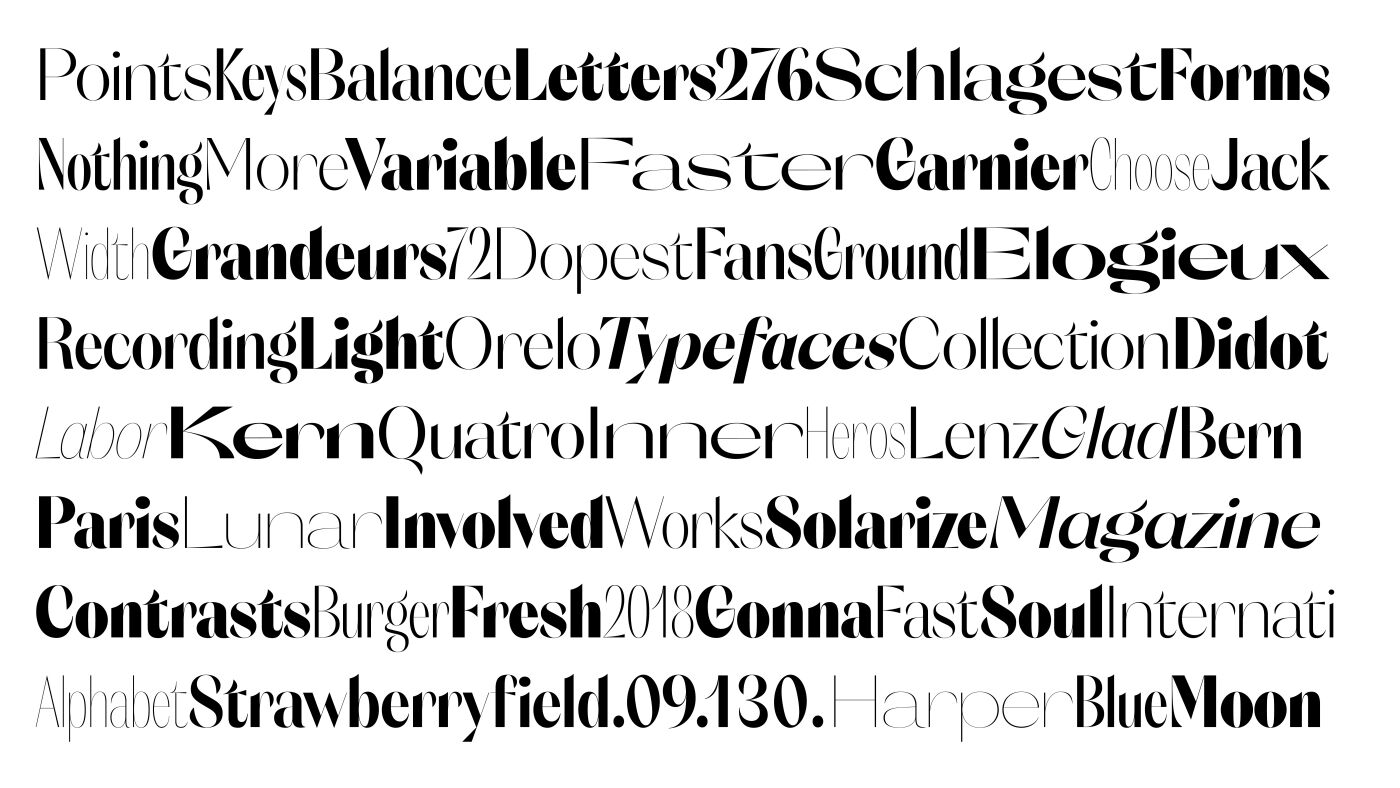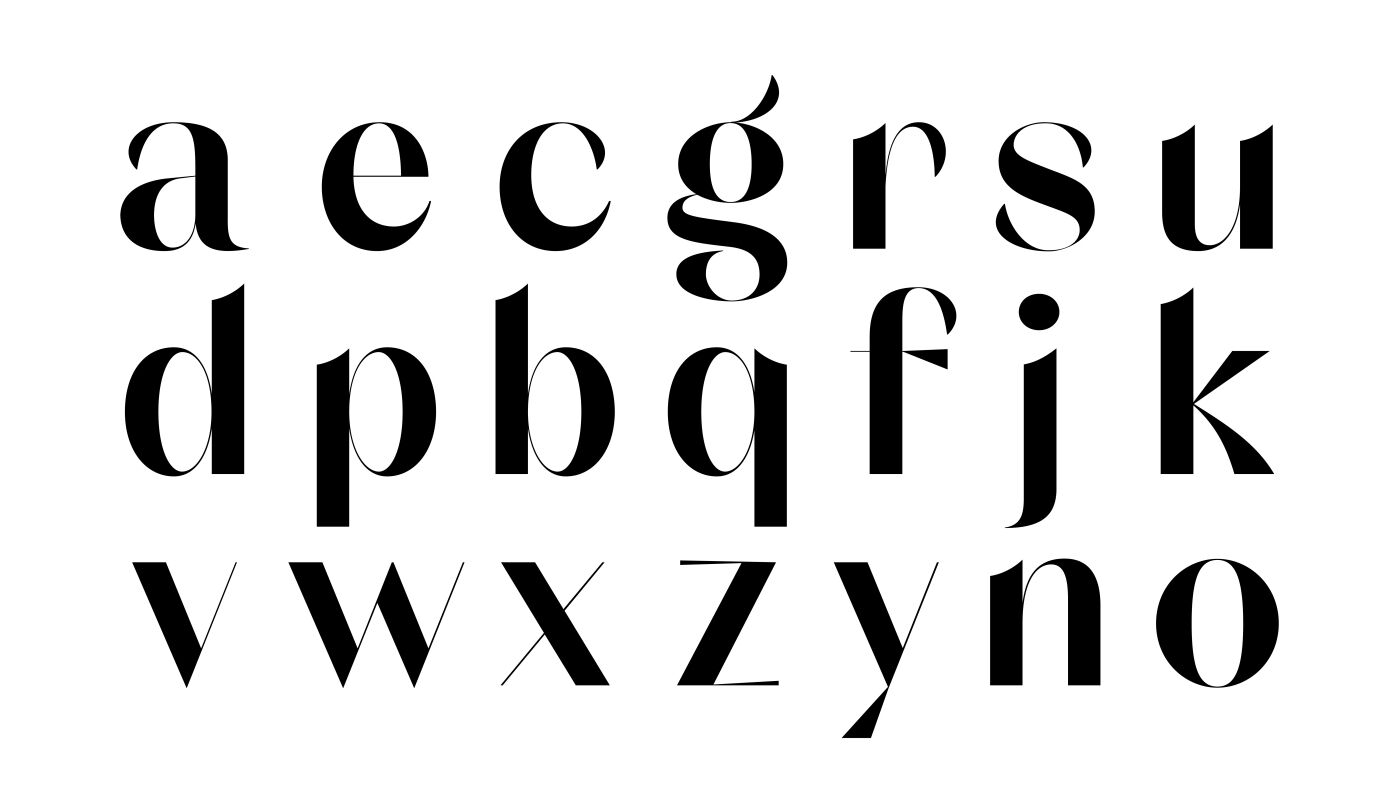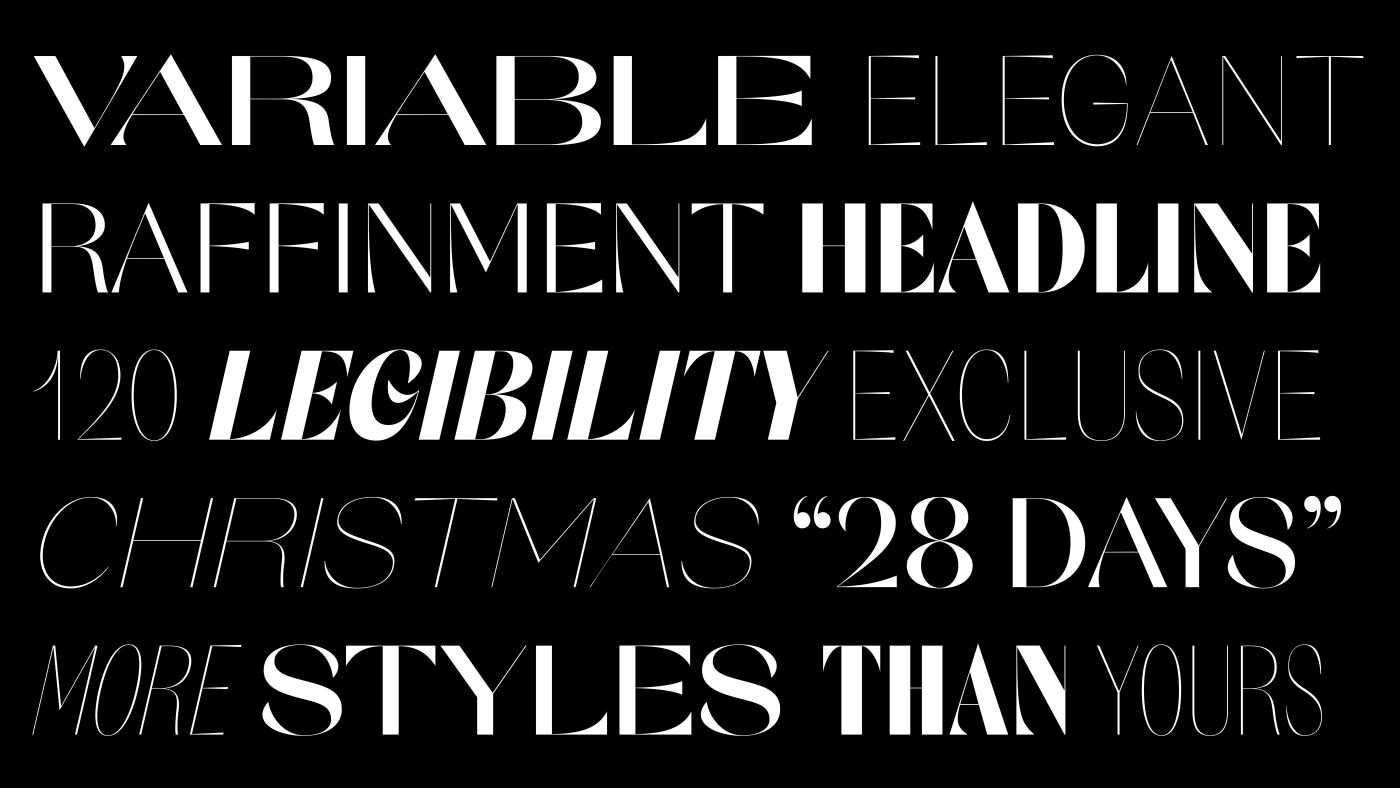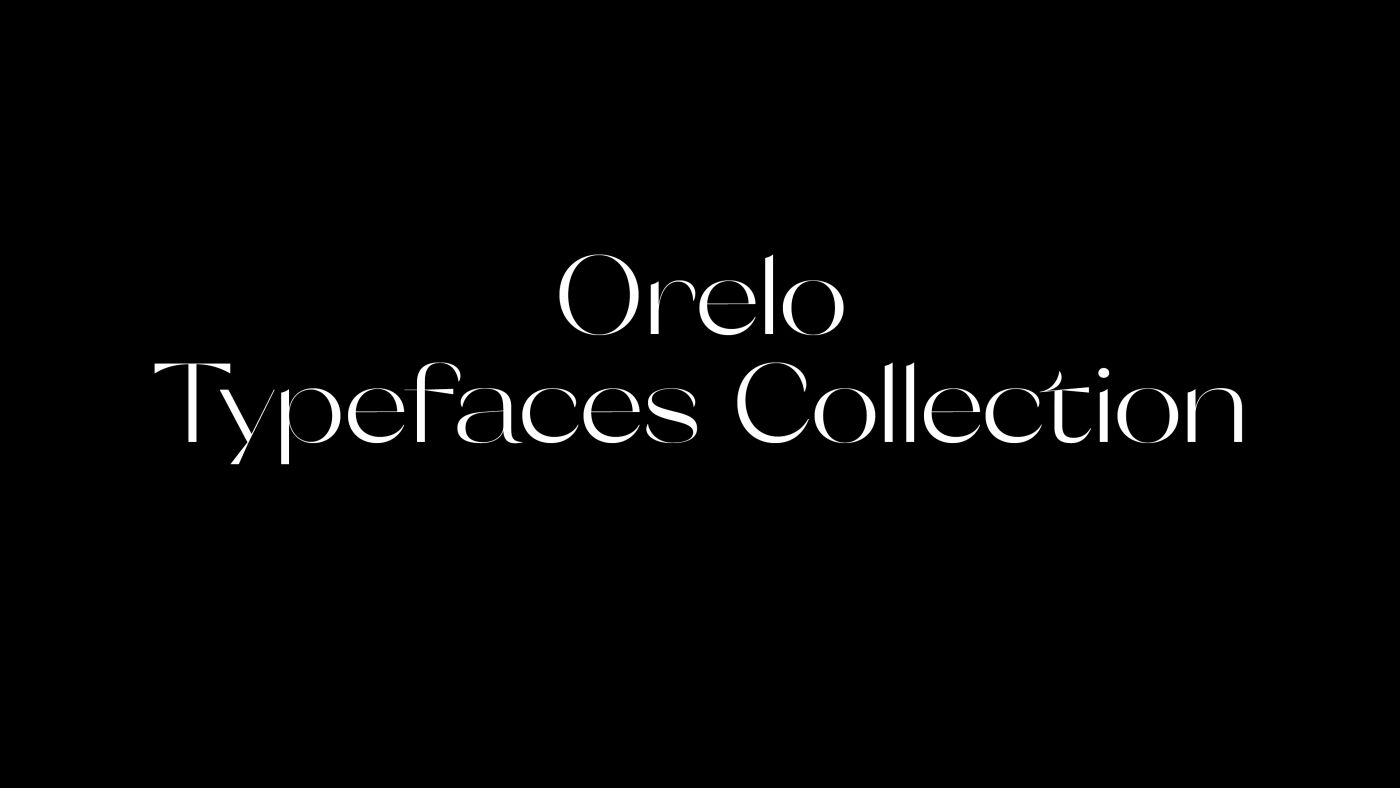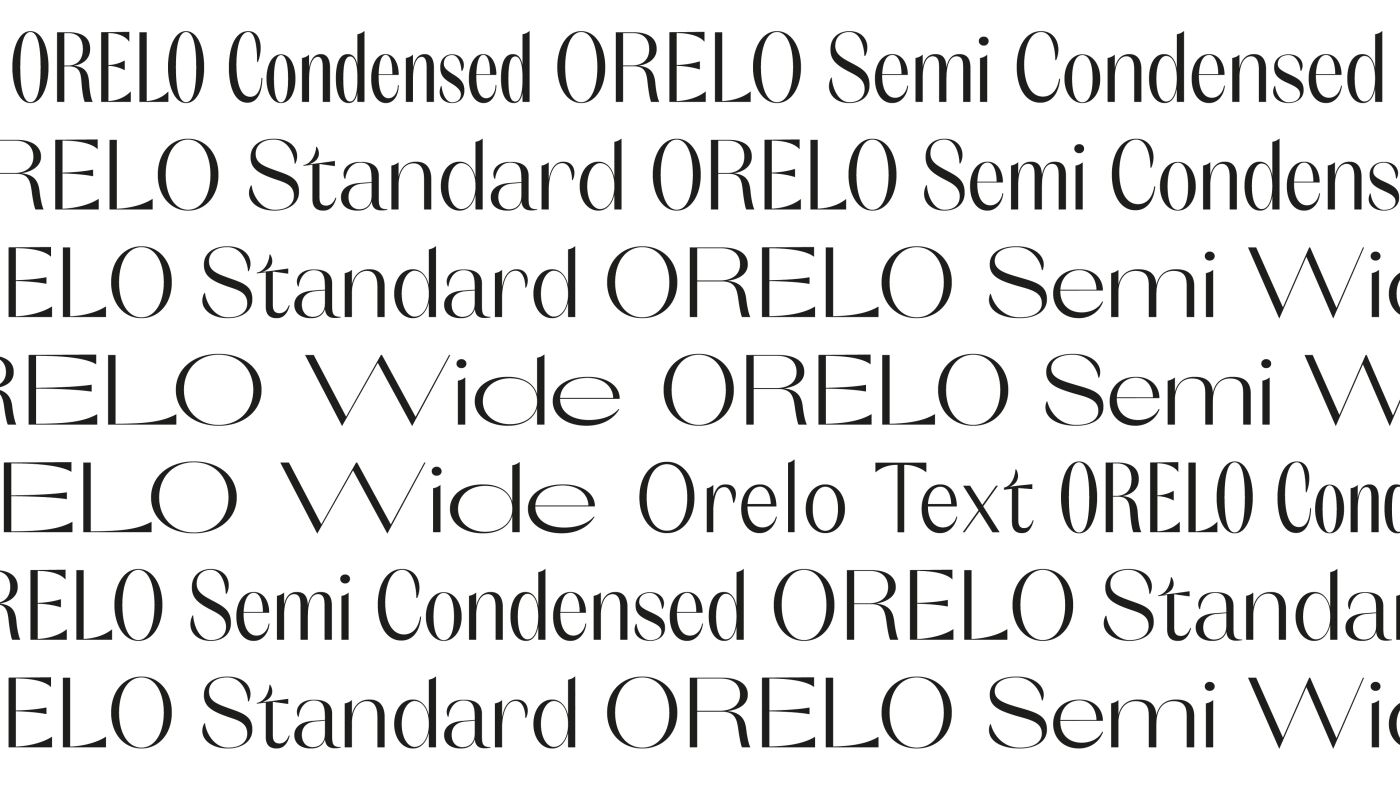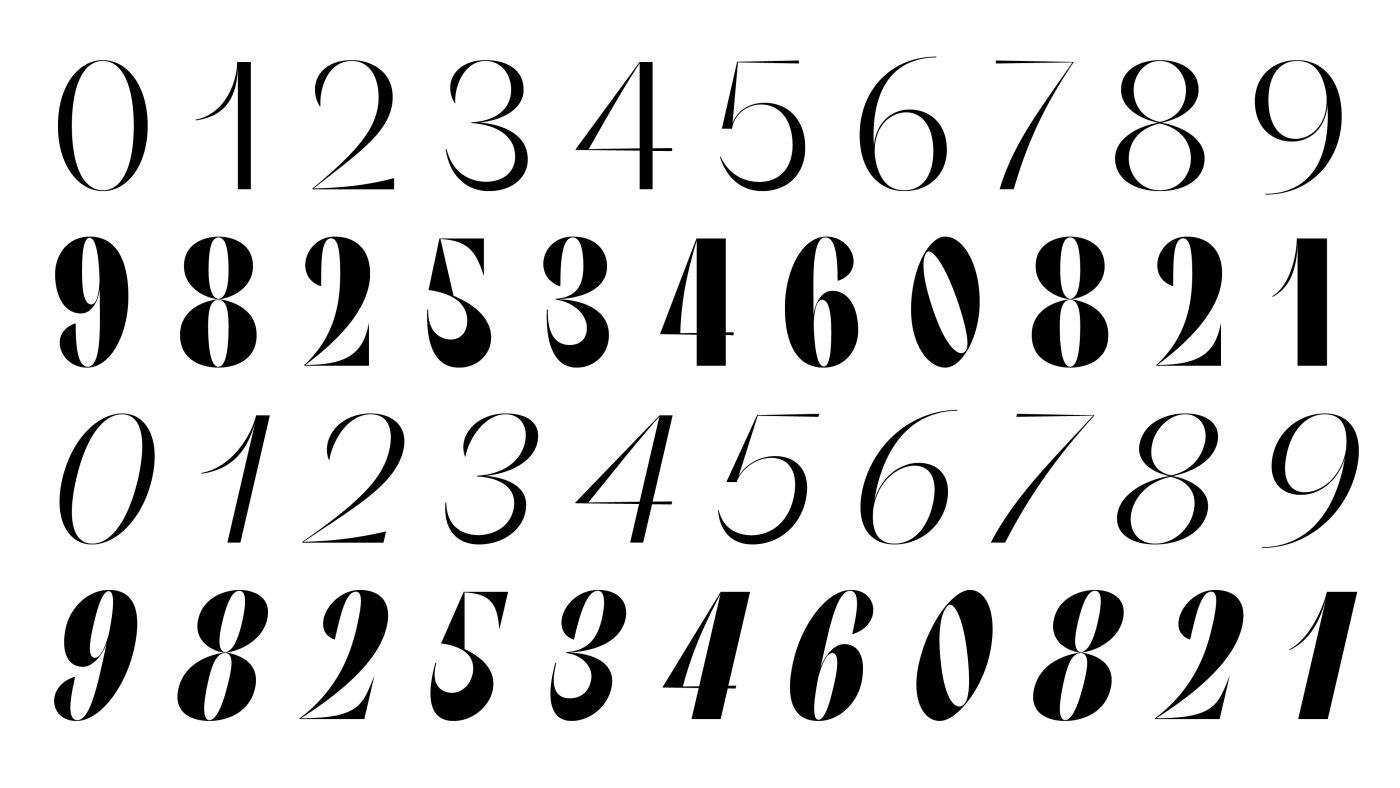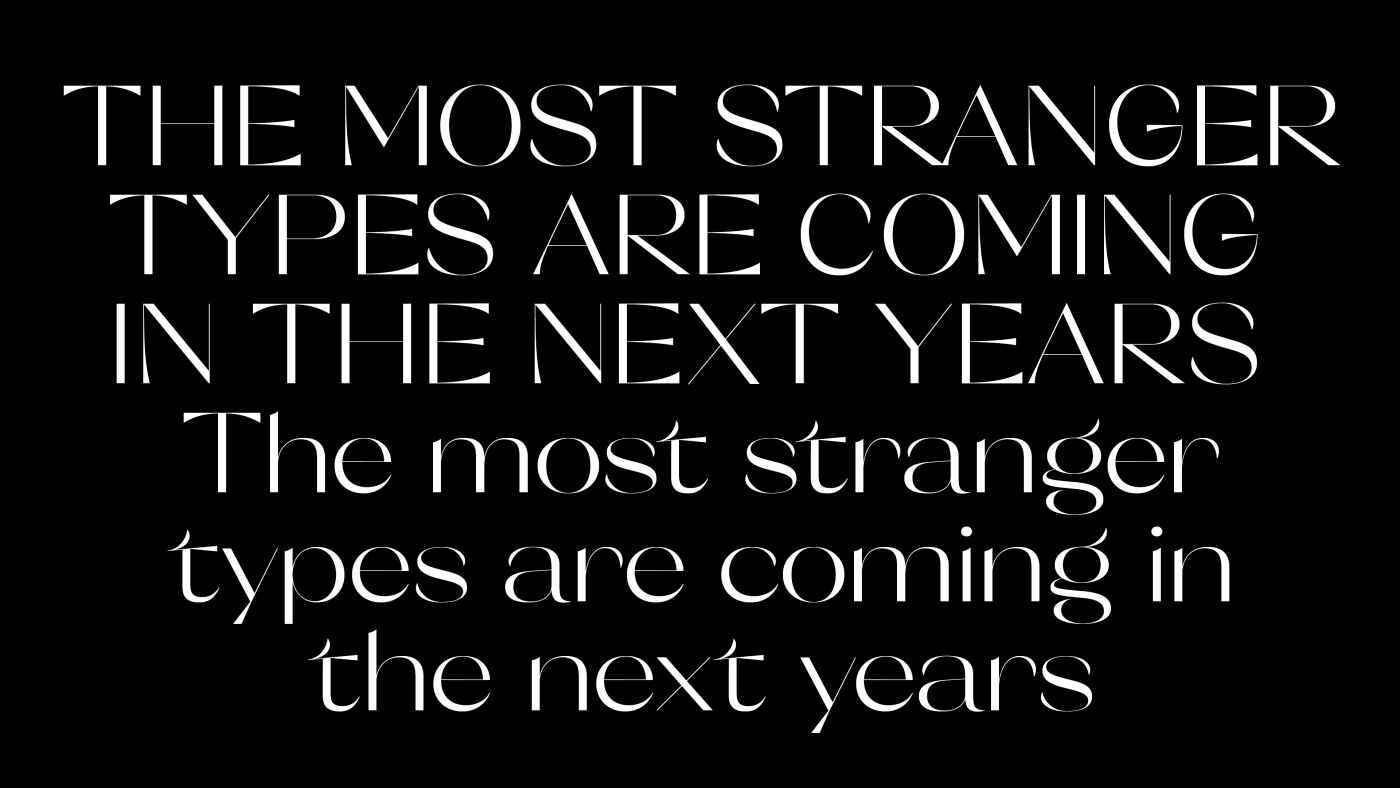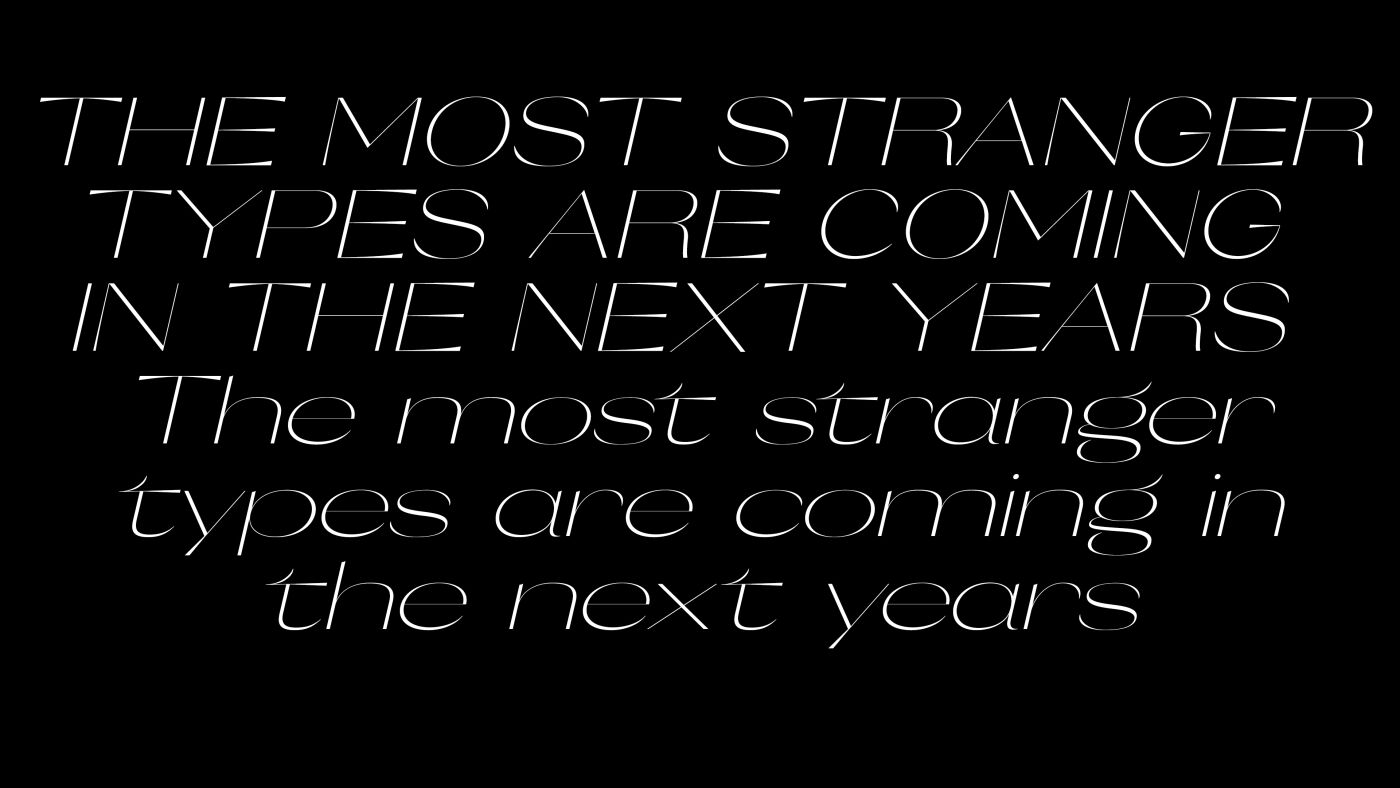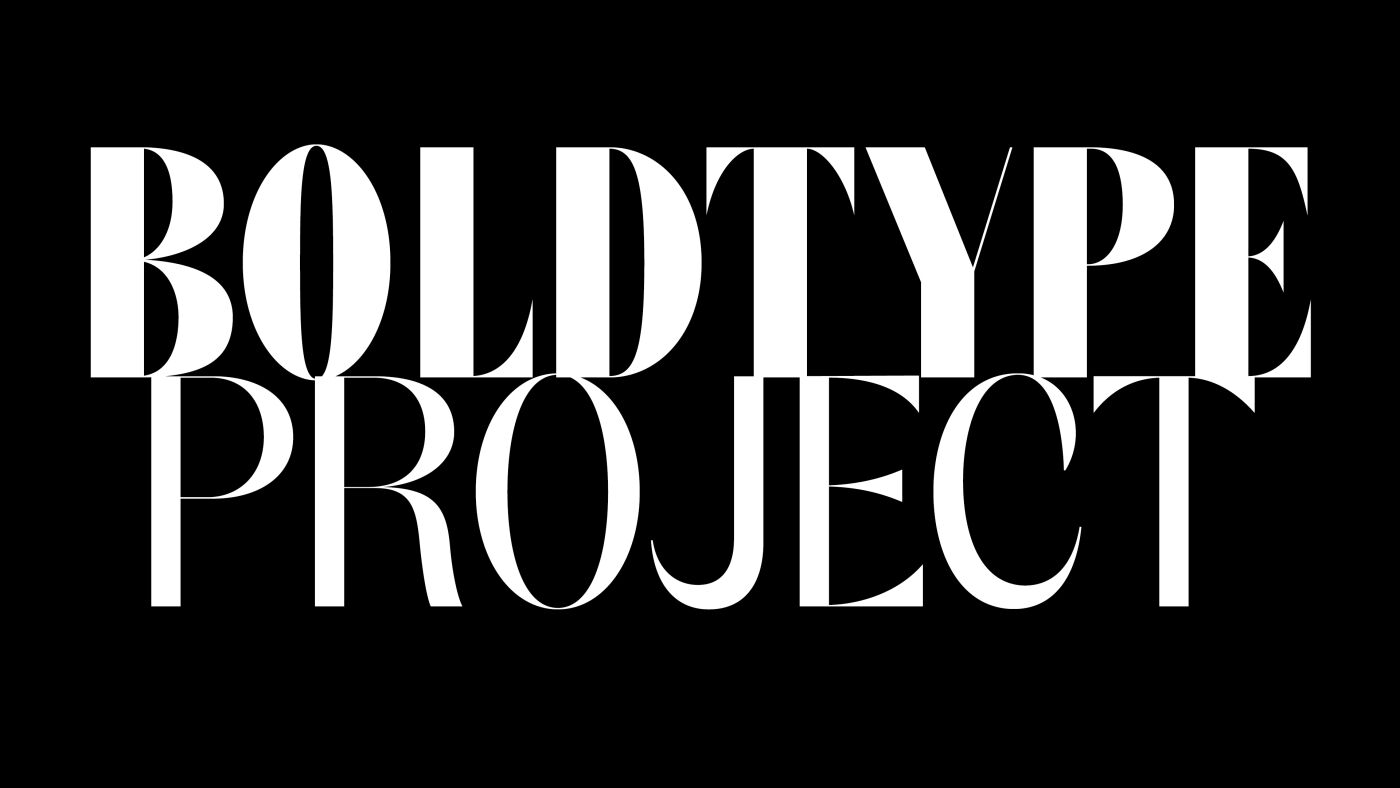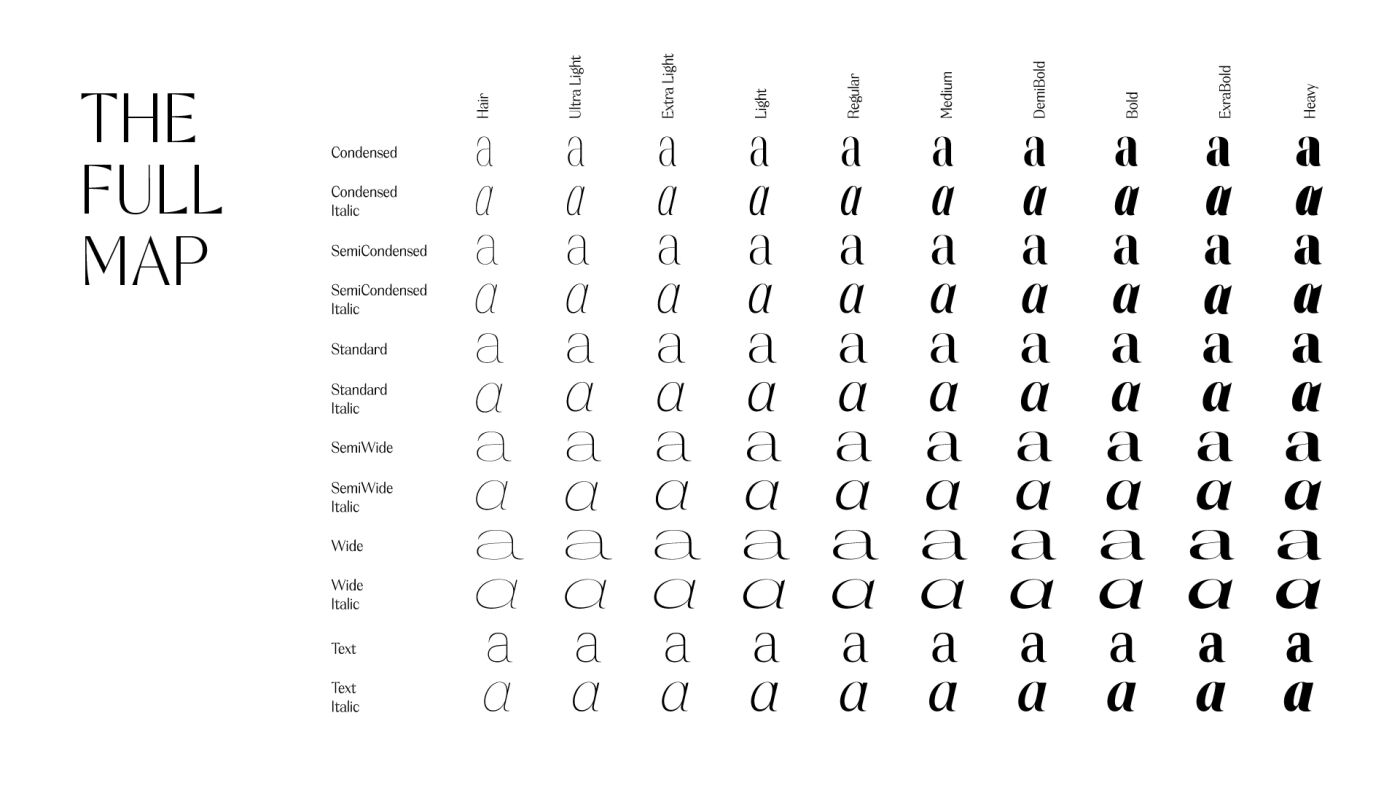
Orelo Typefaces Collection
Orelo est un projet initié dans le cadre de "Bold Type" (kickstarter/étapes: magazine).
C'est plus qu'une typographie, c'est une famille typographique développée en Variable-Font. Les variations se font sur 3 axes : largeur, graisses et italiques. Elle propose 120 styles, du Condensé Hair au Large Heavy avec leurs italiques respectifs ainsi qu'une version spéciale pour les textes longs. C'est une typographie inspirée des Didots françaises mais proposant une nouvelle approche de dessins. Équilibrée, contrastée aux formes contemporaine, Orelo est destinée aux titrages et textes courts.